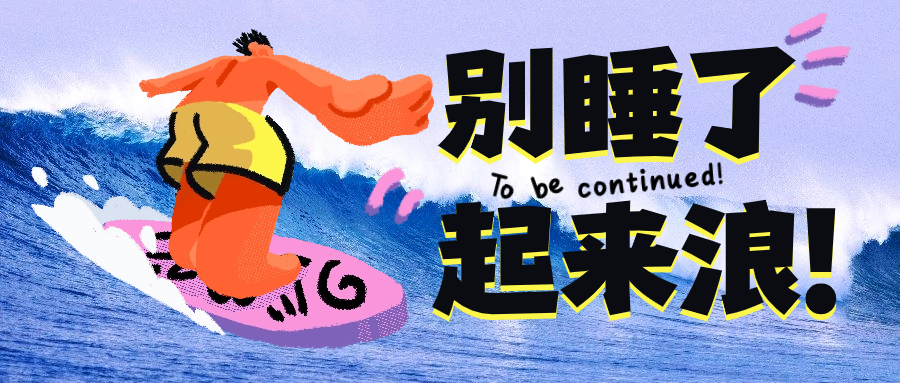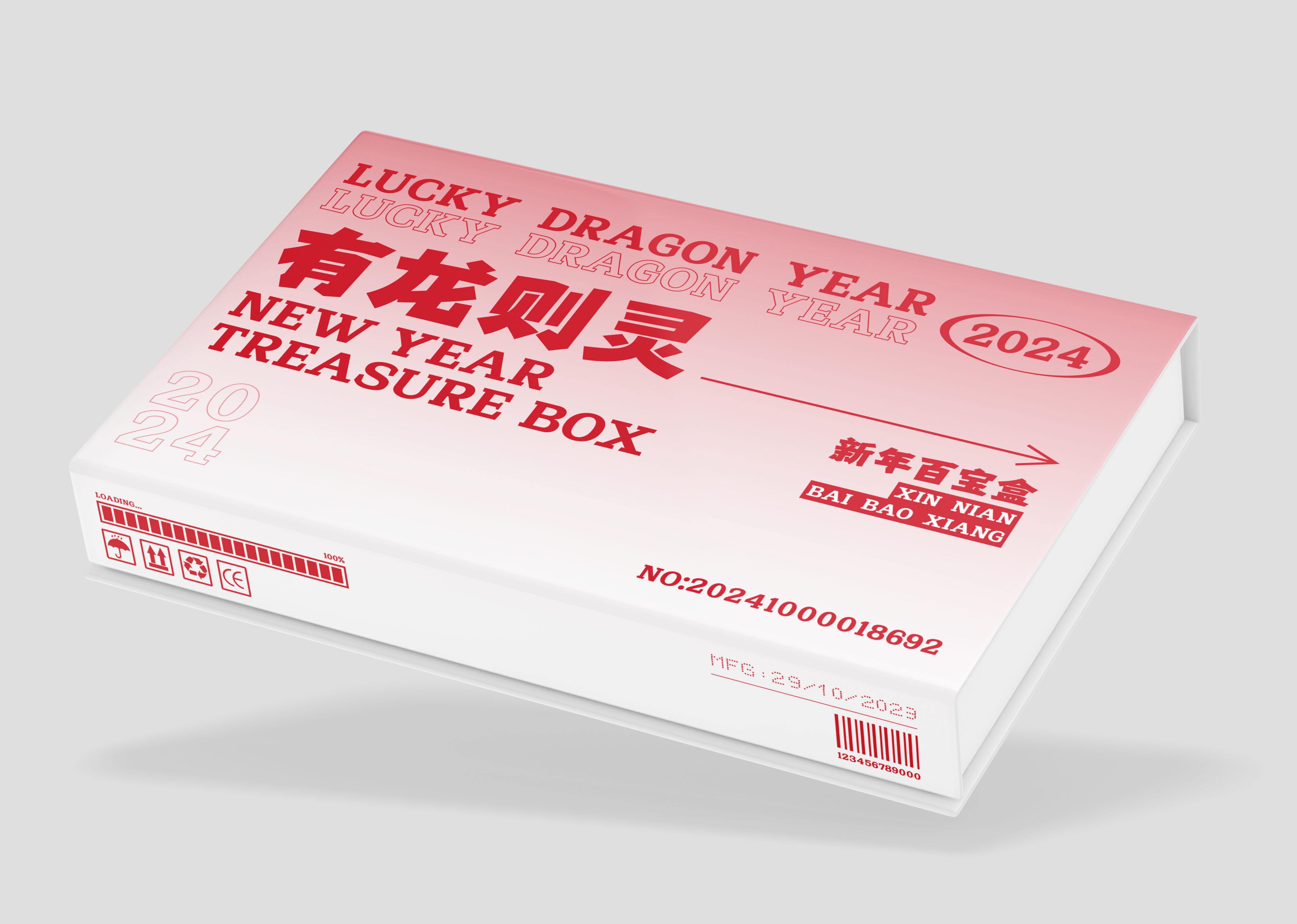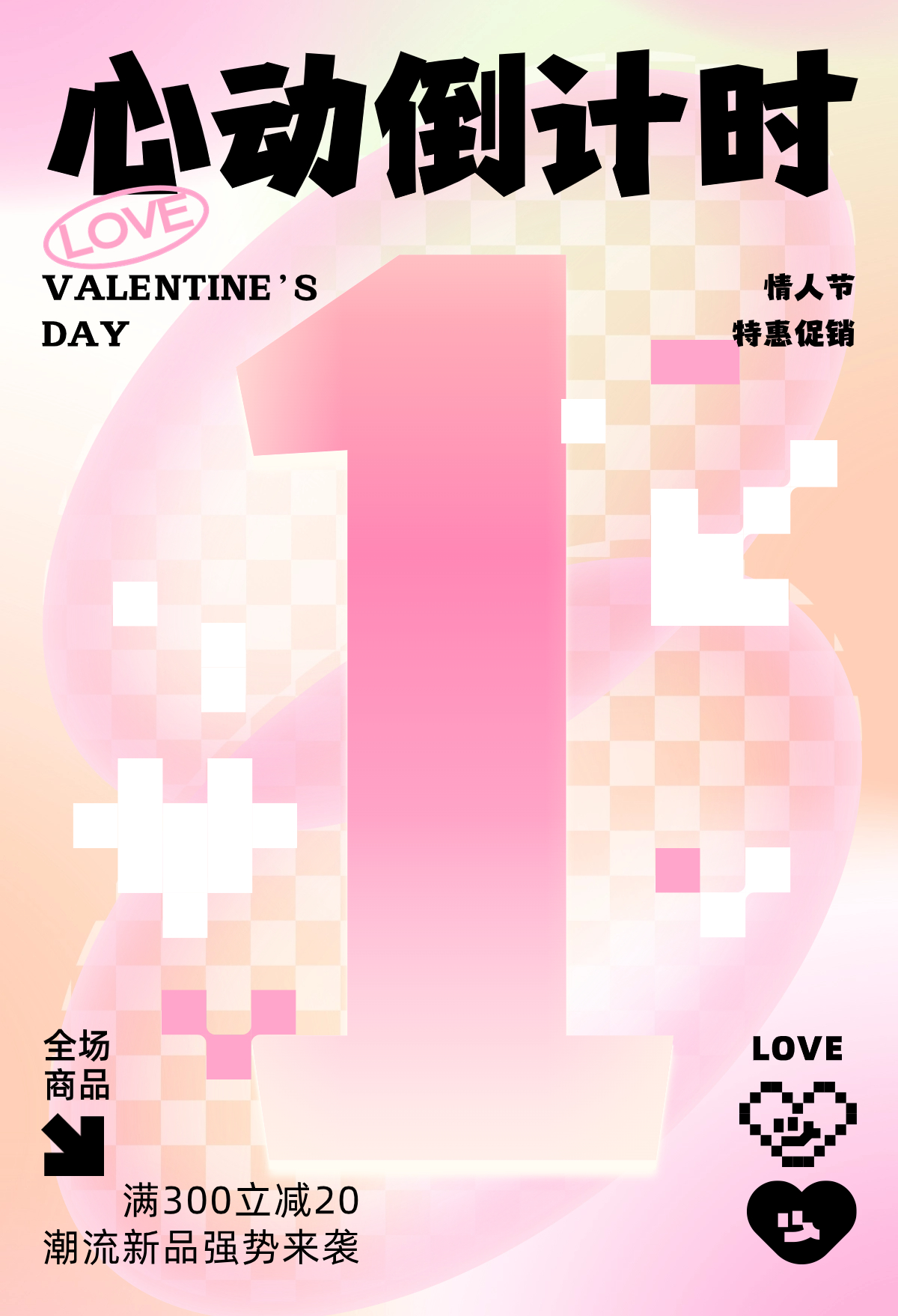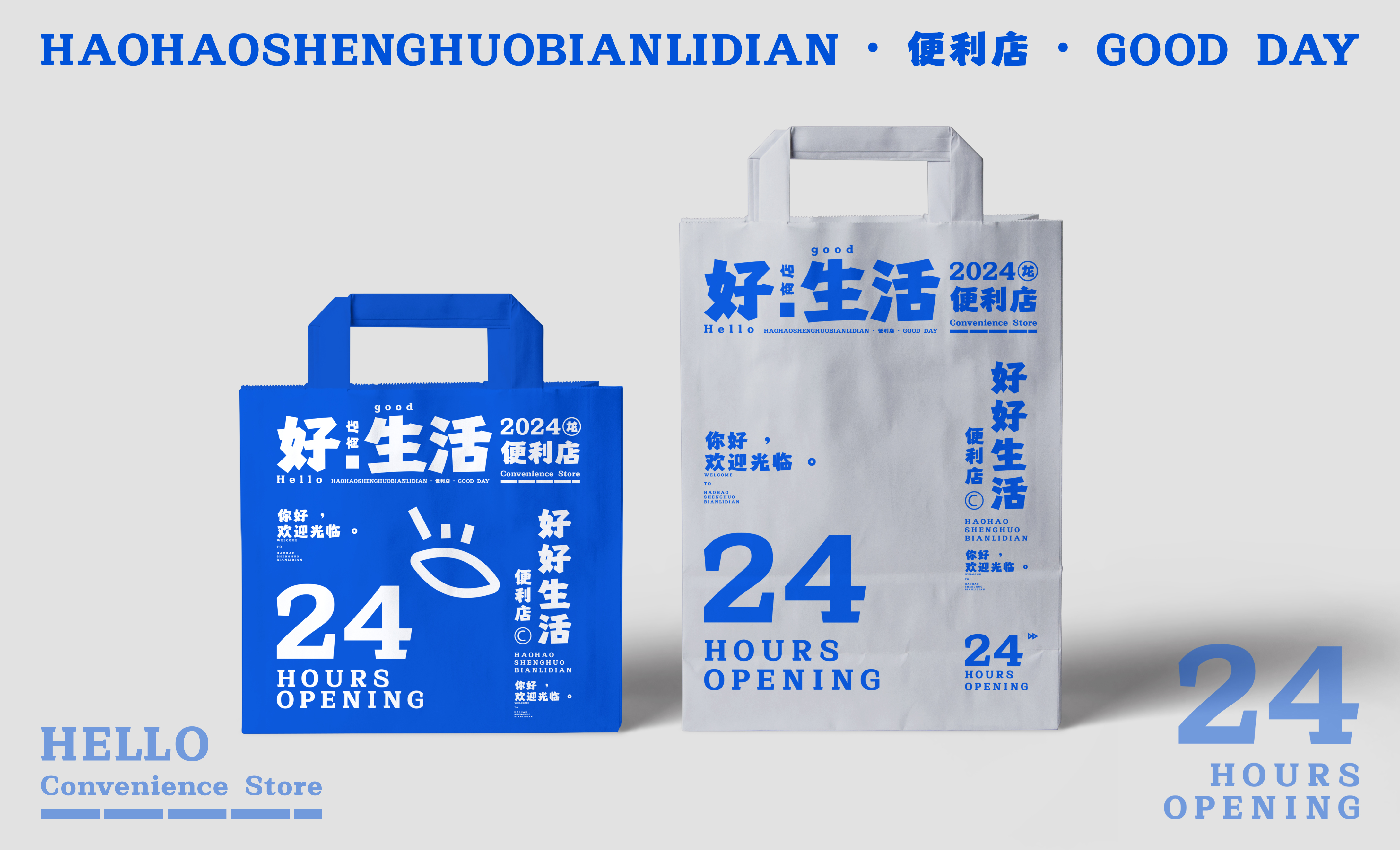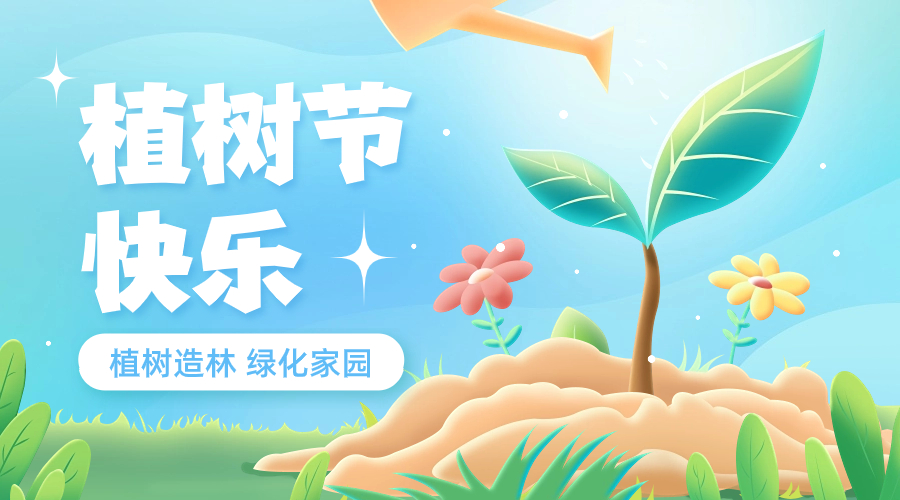
兵克楷黑体
兵克楷黑体,兵克楷黑体,巧妙地将楷书的端庄优雅与黑体的稳重现代感融为一体,其结构紧凑而不失开阔,笔画流畅而不失力度,使得整体字体在视觉上既显得庄重典雅,又不失现代设计的简洁明快,形成了一种独特的视觉张力。楷黑体适用多种设计场景,包括但不限于:标志设计、包装设计、广告设计、印刷品设计。
兵克楷黑体字体介绍